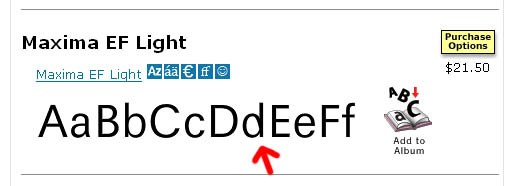
Helvetica, Univers oder ähnliche mit Minuskelziffern?
nach dem Osterwochenende abrupt ins kalte Wasser geworfen bin ich konfrontiert mit der Frage einer Kollegin: "Welche der Helvetica ähnliche Schrift hat Minuskelziffern?", und ich bin spontan überfragt.
es gab einmal eine abgewandelte form der helvetica – die helwissia.
ansonsten die akzidenz grotesk (allerdings nur in der light mit minuskelziffern von spiekermann himself) und die die ff bau.
Hmm, danke für die Tipps, aber ja: die meisten sind zu weit weg von der Helvetica. Es müsste wirklich eine statische Serifenlose sein.
Ist das denn eine Marktlücke?
Ich starte dann mal unauffällig Fontlab...
hier mal ein bild der helwissa
Hm. Aus dem Bild kann man (ich?) jetzt schwer auf den praktischen Einsatz schließen, aber ich vermute mal, mir würde es so ergehen wie mit anderen »Mediävalziffern«, die eigentlich nur gestauchte bzw. verschobenene Tabellenziffern sind: die stören mich im Text noch mehr als die normalen Tabellenziffern gestört hätten.
Wenn ich Mediävalziffern will, dann doch um des Gesamtbildes willen und dann müssen die richtig dafür gestaltet sein. Aber vielleicht ist das (wie so vieles) Geschmackssache.
Die Corporate S verfügt ja auch über OSF und SC, da ist vielleicht der Abstand zu den Amtgrotesken nicht so groß.
Wie wärs mit der Maxima von Wunderlich?